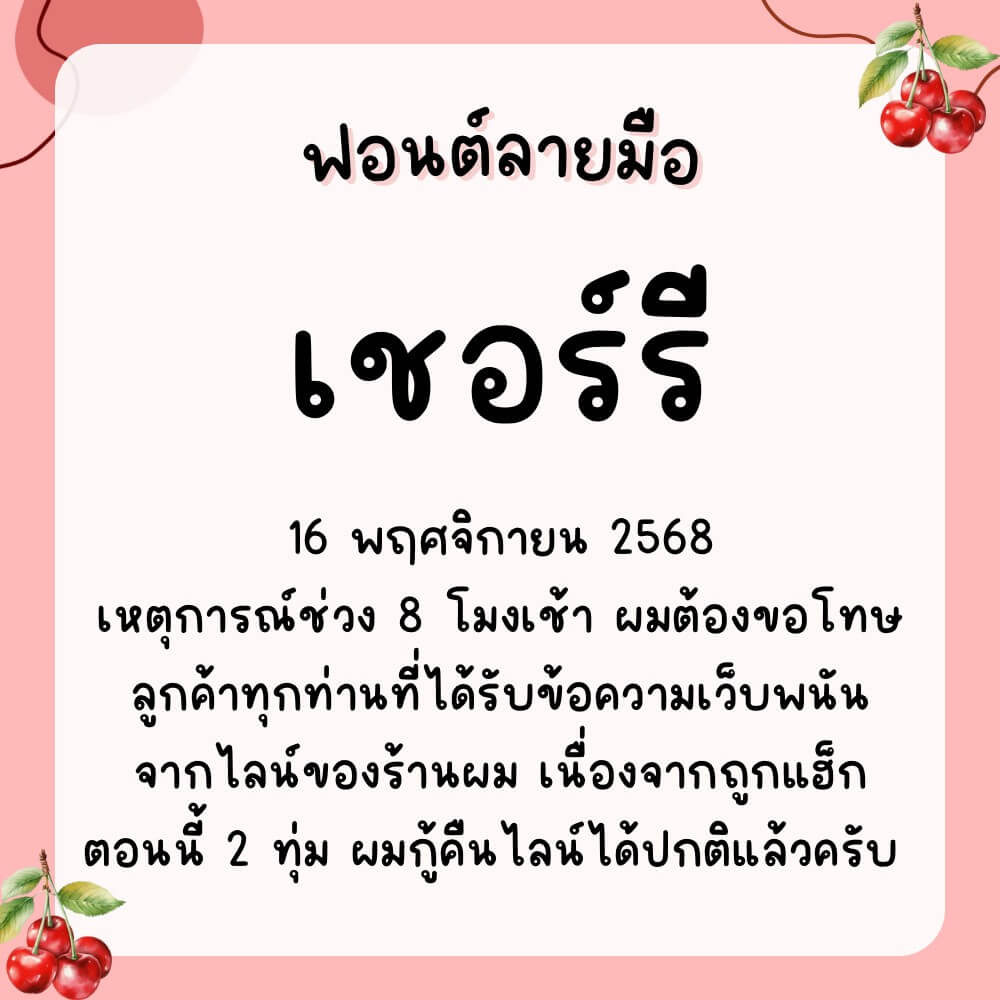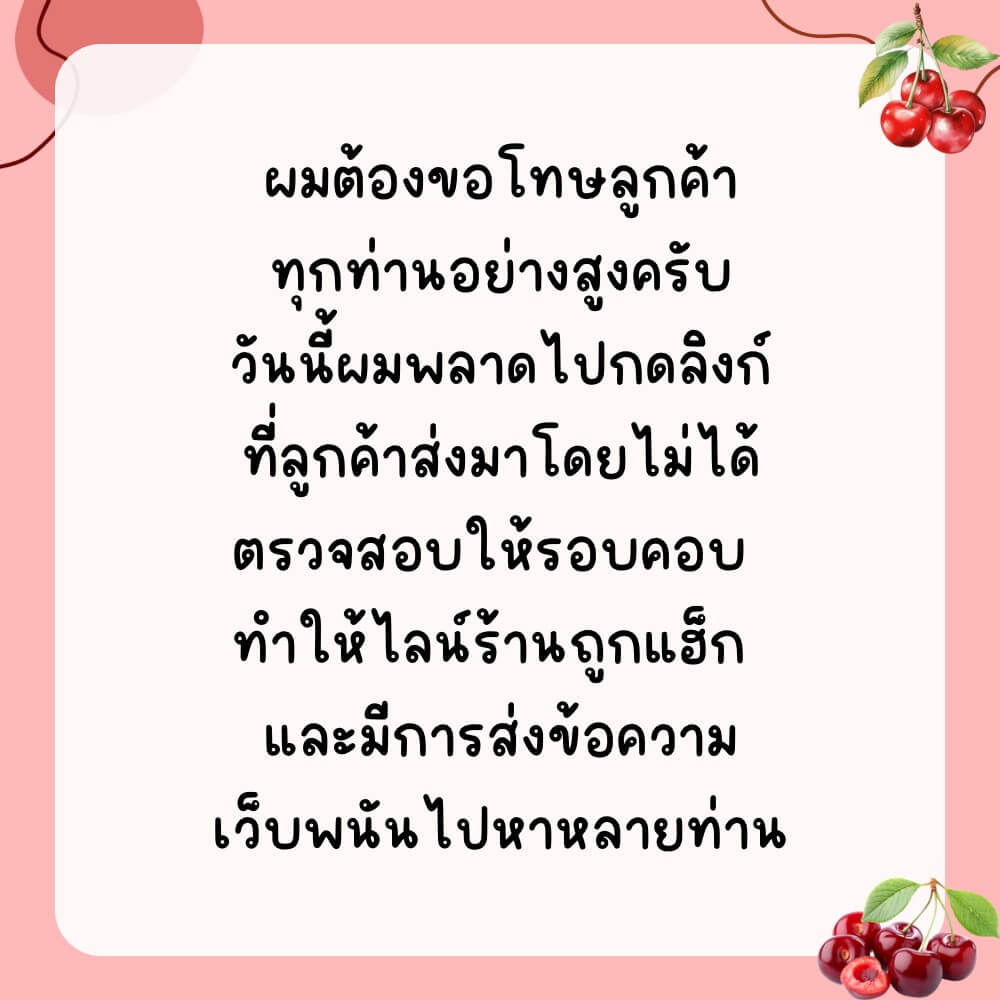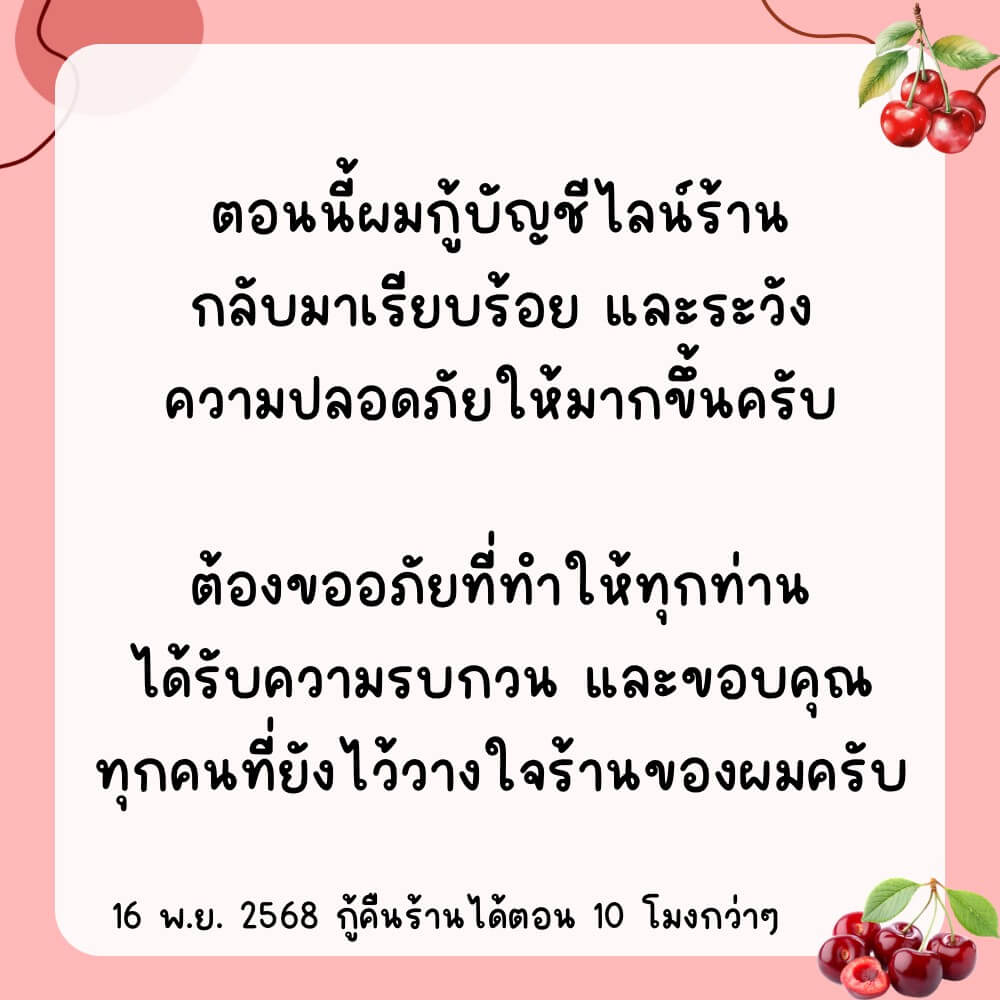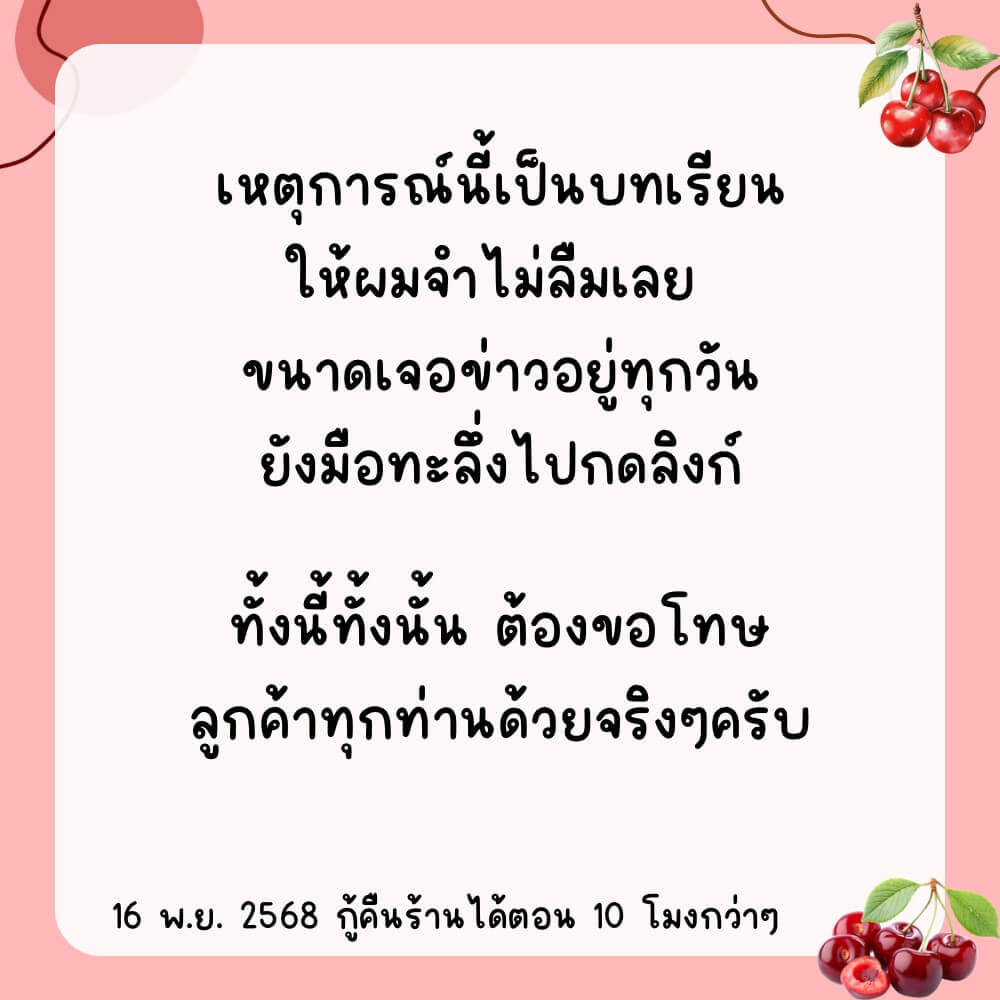
ฟอนต์ลายมือ เชอร์รี่– แจกฟรีสำหรับทดลองใช้งานแบบส่วนตัว เวอร์ชันทดลอง (Demo)
- ได้ฟอนต์ 3 ขนาด คือ ขนากปกติ/หนา/บาง
- ตัวหนังสือปกติ ไม่มีตัวโปร่งปน
เชอร์รี่ (LMF Cherry)